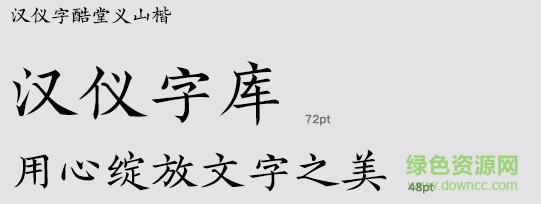
漢儀字酷堂義山楷是一款漢儀字庫中經(jīng)典的楷體字體,用這款字體進(jìn)行排版你會(huì)發(fā)現(xiàn)非常的規(guī)矩整齊,看上去非常賞心悅目,有需要?dú)g迎下載使用!
漢儀字酷堂義山楷字體適用于文章書寫應(yīng)用,該字體非常經(jīng)典古老,盡顯中國(guó)文學(xué)字體的魅力。